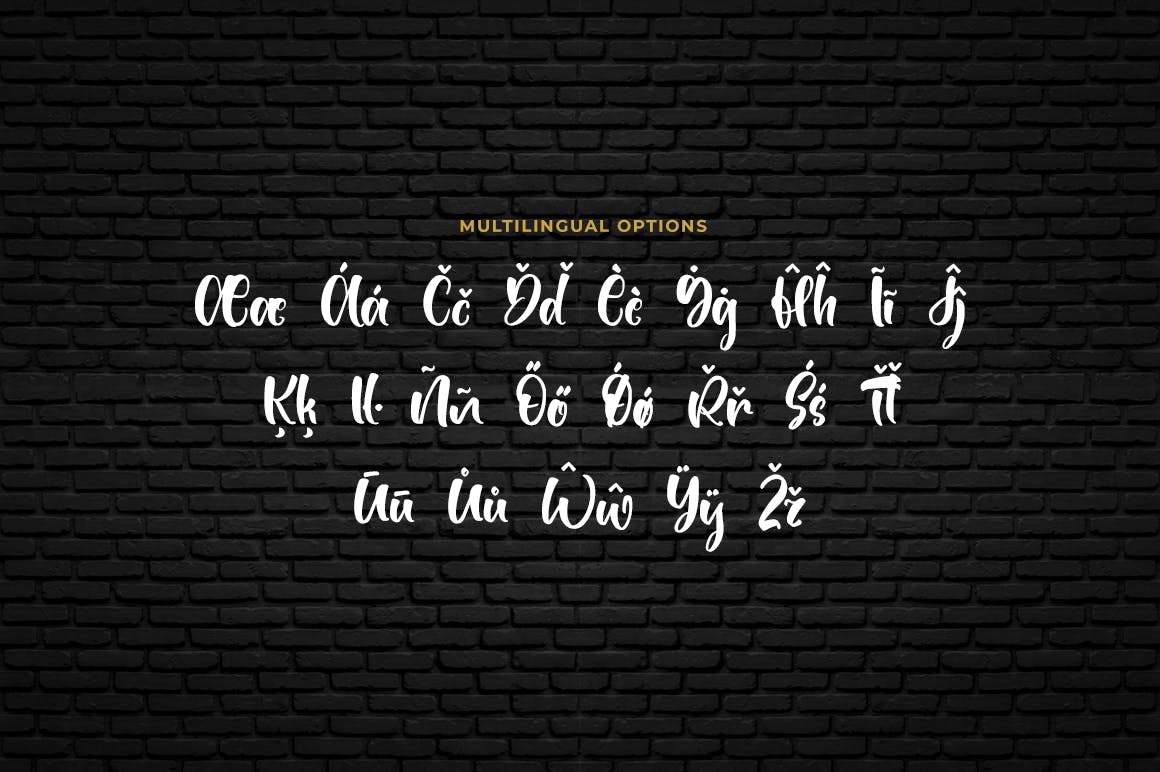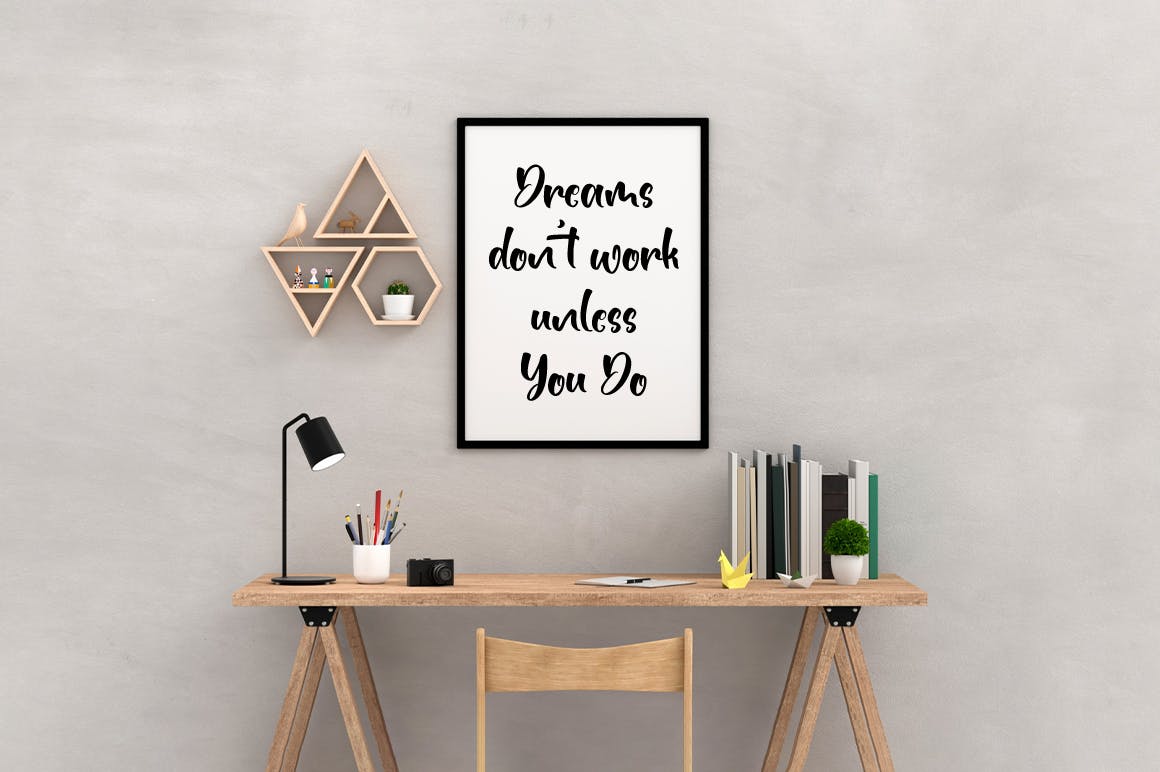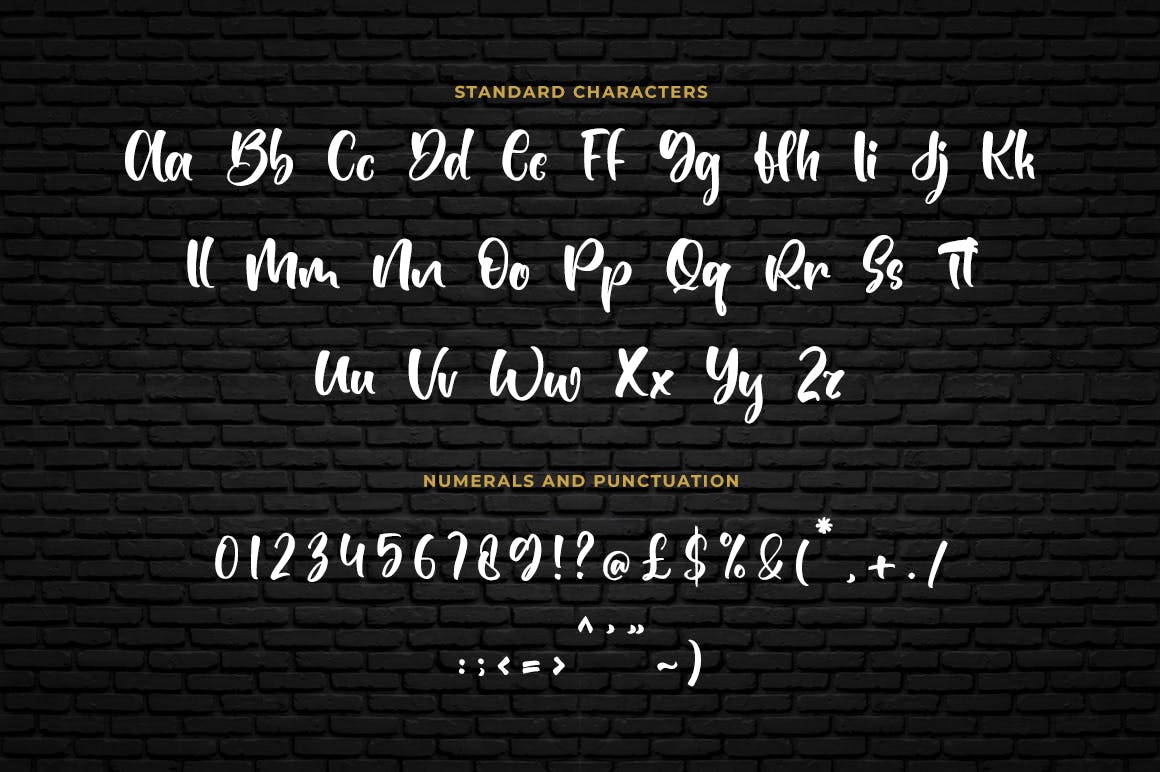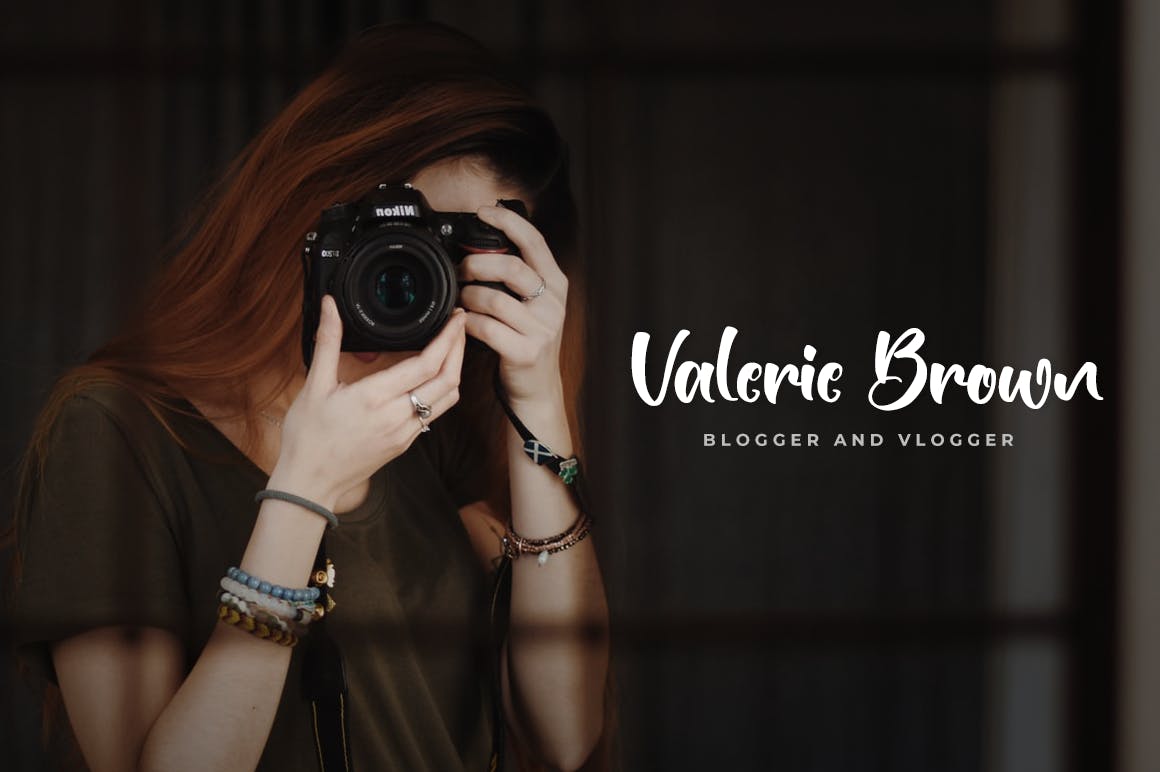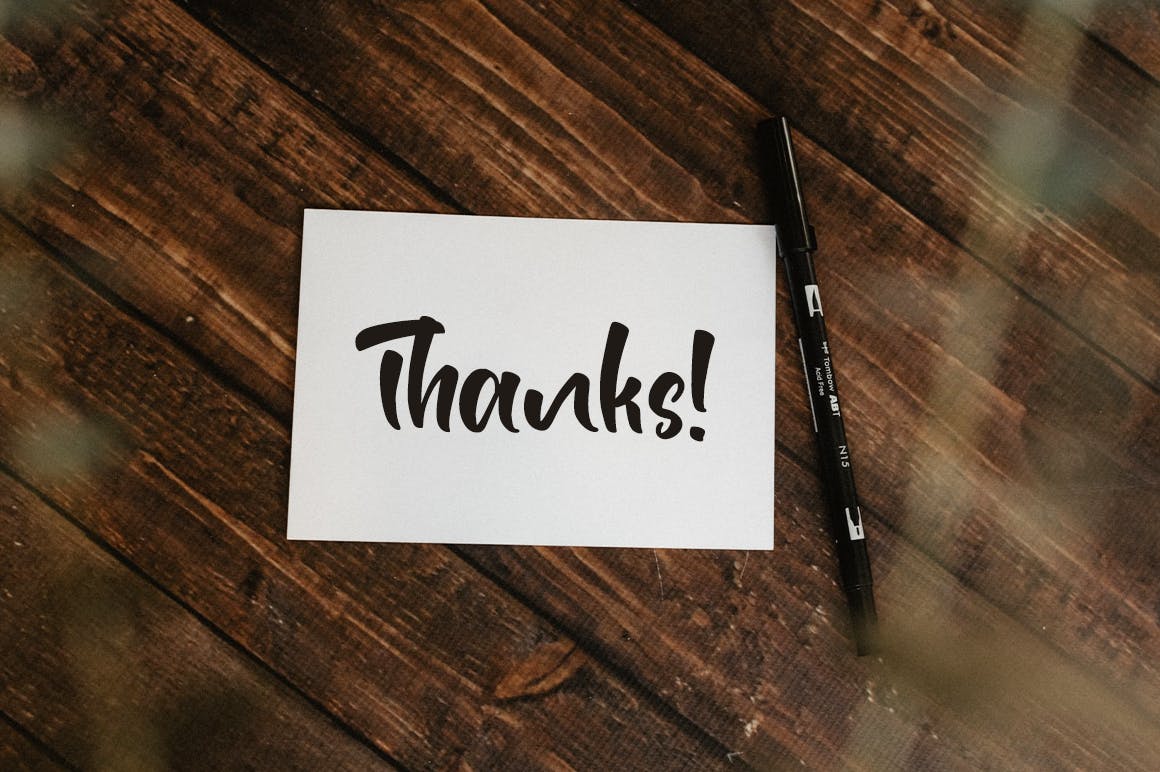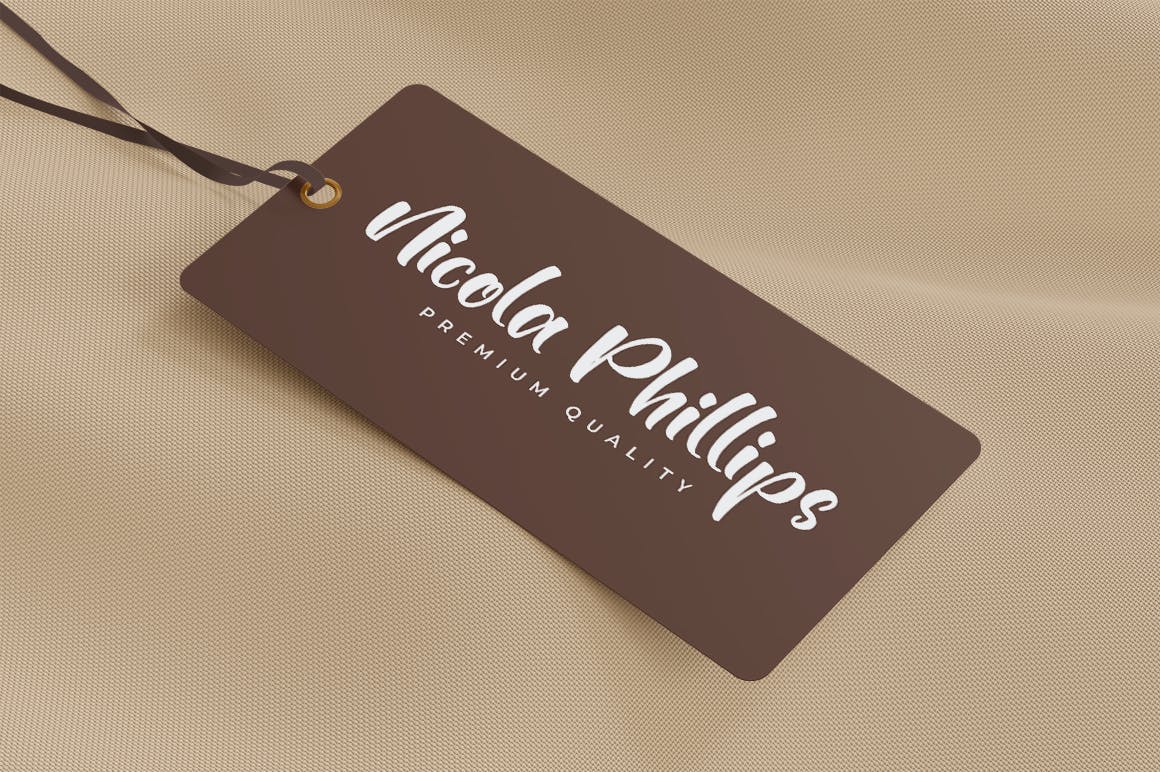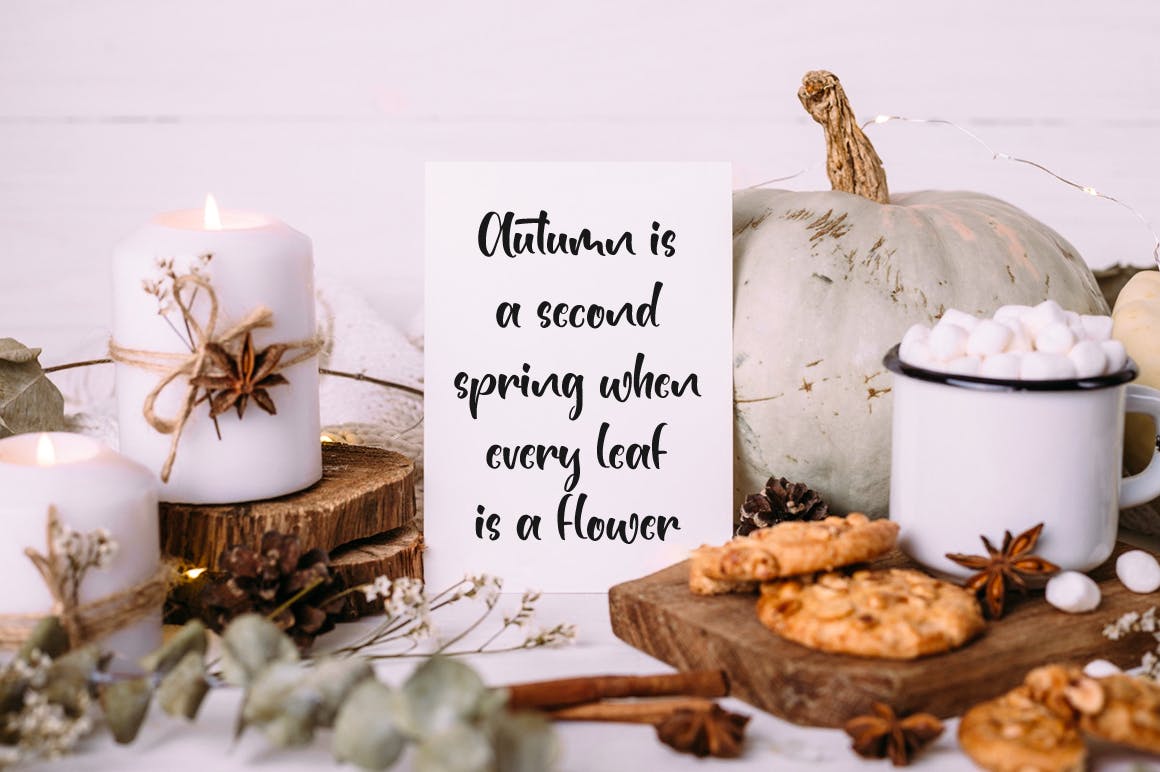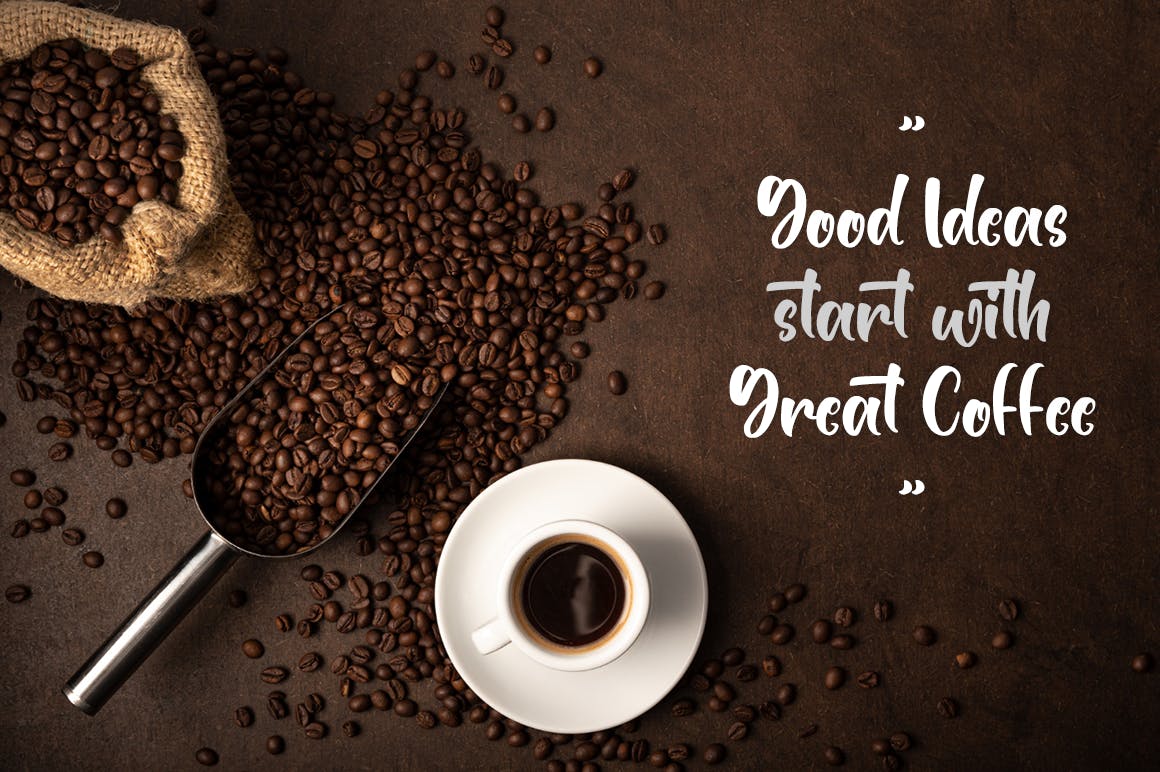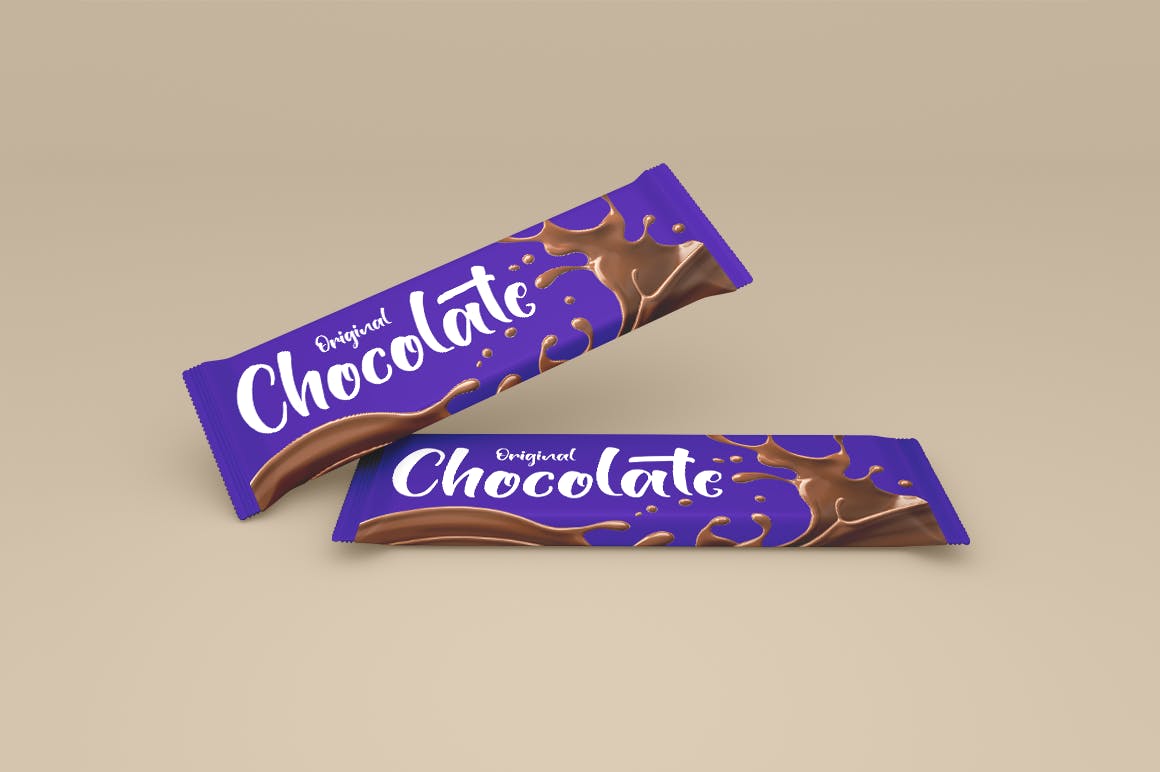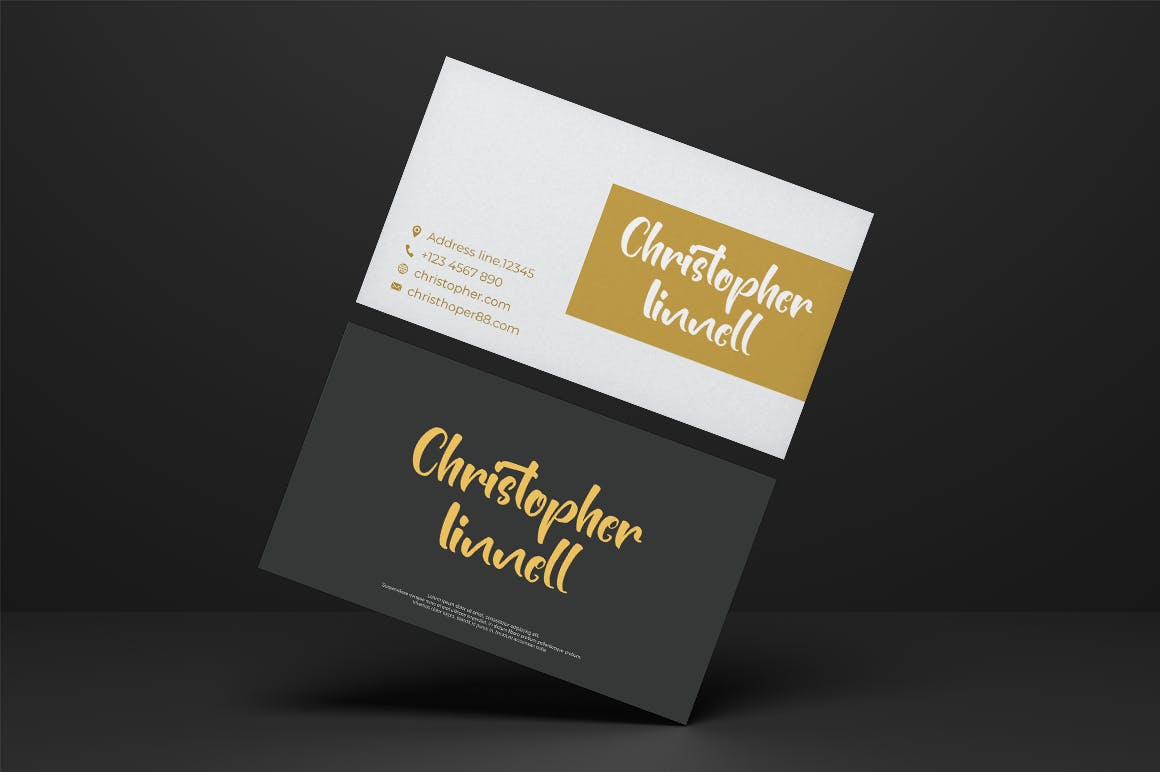
Reymond یک فونت اسکریپت زیبا و برجسته است. با سبک فوقالعاده متنوع آن عشق بورزید و از آن برای ایجاد دعوتنامههای عروسی زیبا، آثار هنری ایستگاههای شیک، پستهای جذاب در شبکههای اجتماعی و بسیاری موارد دیگر استفاده کنید!